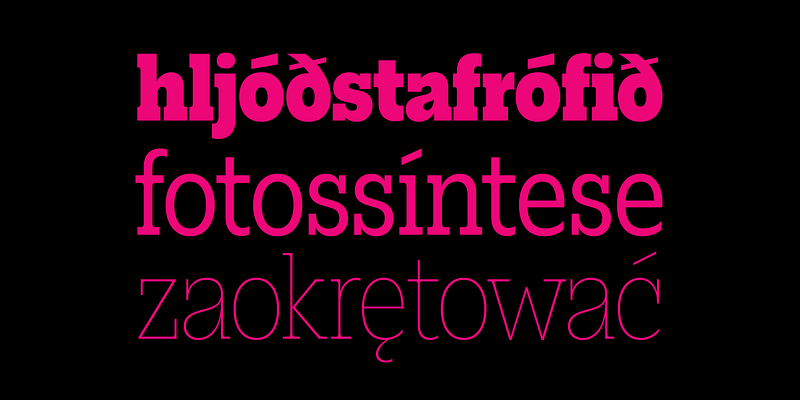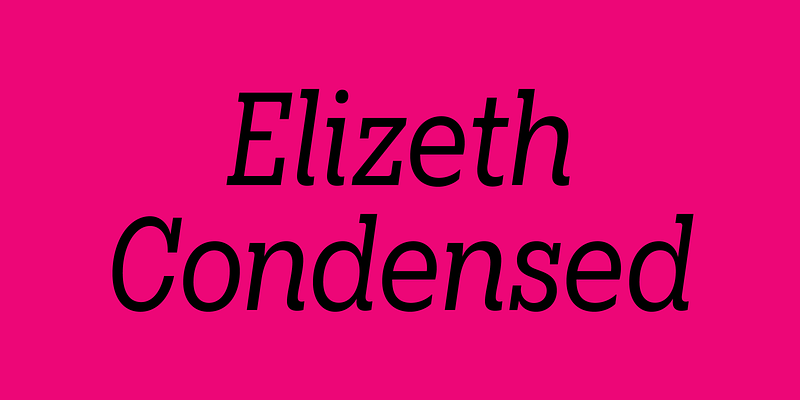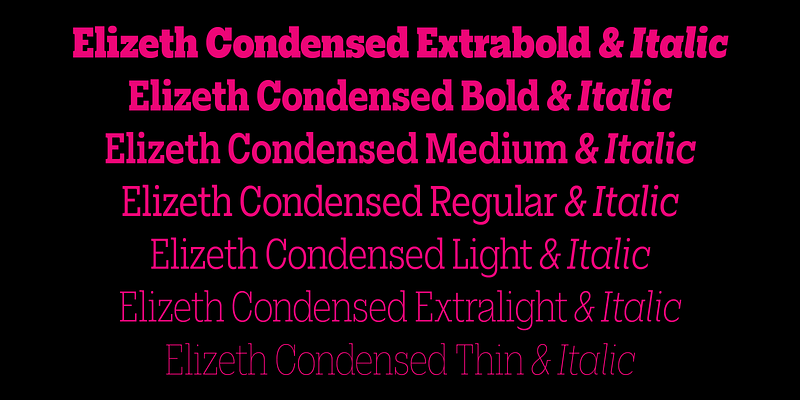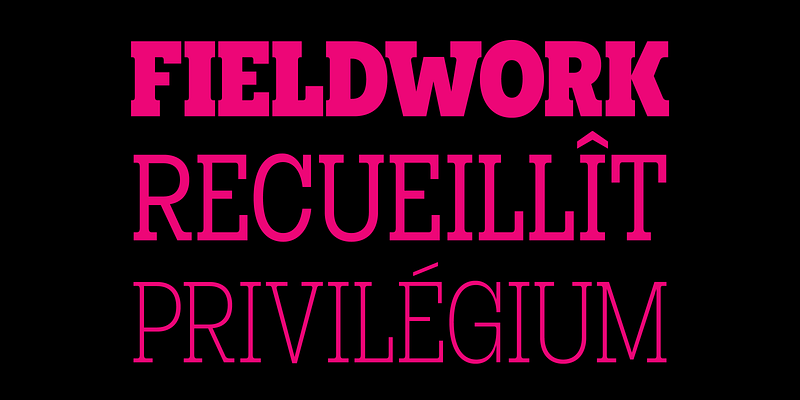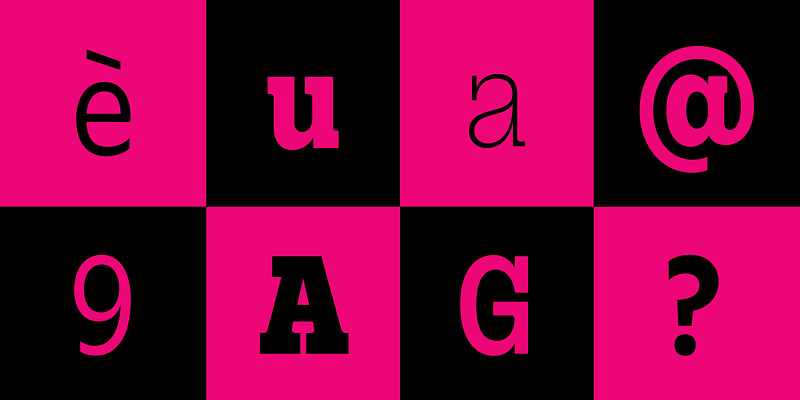
Elizeth ist das Gegenstück zu Ofelia mit Serifen. Es handelt sich um eine sehr vielseitige Schrift in zwei Breiten und sieben Stärken für die verschiedensten Einsatzgebiete. Die normale Stärke ist ein geometrischer Block, der an den Rationalismus des frühen 20. Jahrhunderts erinnert und so in einen Dialog mit Schriften wie Rockwell eintritt – allerdings mit eckigen Serifen. Die Schrift verfügt über eine echte Kursivschrift, umfassende Sprachunterstützung und bestimmte OpenType-Optionen wie Kapitälchen, Mediäval- und Tabellenziffern.